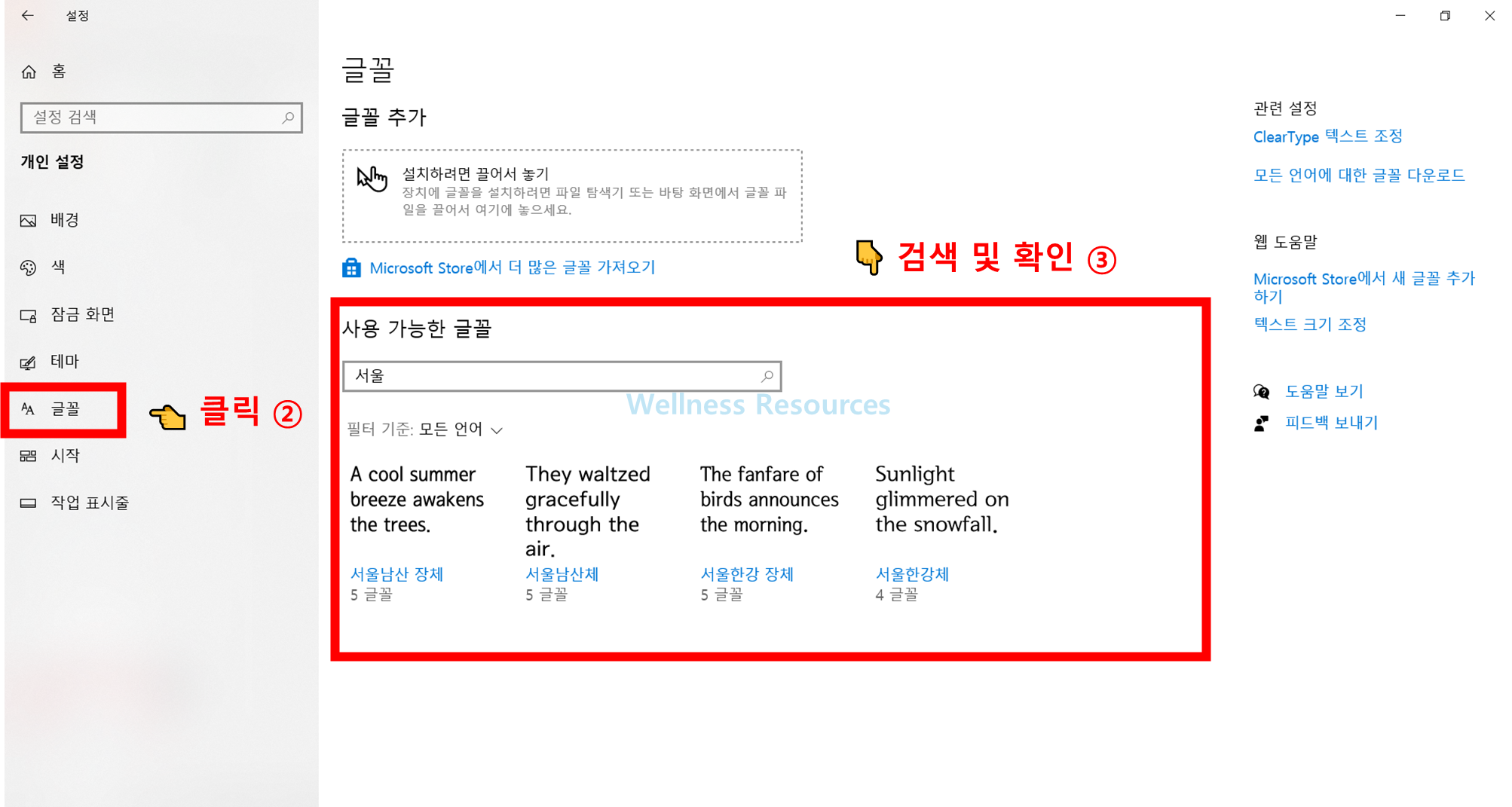
서울남산체와 서울한강체는 서울시가 개발한 대표 무료 서체로, 공공기관 문서부터 웹·모바일 디자인까지 폭넓게 활용됩니다. 본문에서는 두 서체의 특징, 활용 사례, 다운로드 경로와 설치 방법까지 자세히 안내합니다. 웹폰트 설정 가이드와 라이선스 표기도 함께 담았어요. 웹폰트 최적화 팁과 적용 예시까지 자세히 안내합니다.
1. 서울남산체의 특징
서울남산체는 2016년 처음 공개된 서체로, 직선과 곡선의 균형 잡힌 조화가 돋보입니다. 전통적인 세리프 요소와 현대적 고딕체의 간결함을 결합해 공문서, 안내판, 광고물 등 다양한 분야에서 사용하기 좋습니다. 글자 형태가 뚜렷해 가독성이 뛰어나며 신뢰감을 주는 디자인이 특징입니다.
| 장점 | 설명 |
|---|---|
| 명확한 가독성 | 글자 모양이 선명해 읽기 편리함 |
| 활용도 다양 | 광고, 간판, 공식 문서 등 다방면에 적합 |
| 세련된 조화 | 세리프 전통성과 고딕의 간결함을 함께 제공 |
3. 서울한강체의 특징
서울한강체는 도시의 상징인 한강에서 영감을 받아 만들어졌으며, 직관적이고 간결한 글자 구조로 특히 디지털 환경에서 강점을 발휘합니다. 온라인 콘텐츠, 모바일 앱, 웹사이트 디자인에 최적화되어 있으며 최신 트렌드와도 잘 맞습니다.
| 디자인 특성 | 설명 |
|---|---|
| 간결한 구조 | 불필요한 장식 없이 직관적 형태 |
| 디지털 최적화 | 온라인 환경에서 가독성 극대화 |
| 현대적 감각 | 최신 디자인 트렌드와 부합 |
4. 활용 사례 비교
서울남산체와 서울한강체는 각기 다른 특성을 갖지만, 모두 공공성과 현대적 미감을 동시에 충족합니다.
| 활용 분야 | 서울남산체 | 서울한강체 |
|---|---|---|
| 공공기관 문서 | 신뢰감과 공신력 전달 | 간결한 전달력 |
| 광고·홍보물 | 전통과 세련미 강조 | 직관적 메시지 전달 |
| 문화 행사 | 지역 정체성 표현 | 현대적 이미지 강화 |
| 디지털 매체 | 웹·앱에서도 사용 가능 | 모바일 UX 최적화 |
5. 디자인 활용 팁
- 공공기관 문서: 남산체로 신뢰성을 강화
- SNS 콘텐츠: 한강체로 간결하고 현대적인 이미지 부각
- 포스터·간판: 두 서체를 혼합 사용해 시각적 변화를 줌
6. 결론
서울남산체와 서울한강체는 서울시가 무료로 배포하는 대표적인 서체로, 전통과 현대를 동시에 담아 다양한 디자인 환경에 활용할 수 있습니다. 공공문서의 신뢰감을 높이고, 디지털 환경에서도 뛰어난 가독성을 제공하는 만큼 반드시 설치해 두고 활용할 가치가 있습니다.
Q1. 서울남산체와 서울한강체의 가장 큰 차이는 무엇인가요?
A1. 남산체는 세리프와 고딕의 조화를 이루며 전통과 신뢰성을 강조하는 반면, 한강체는 간결하고 현대적인 감각으로 디지털 환경에 특화되었습니다.